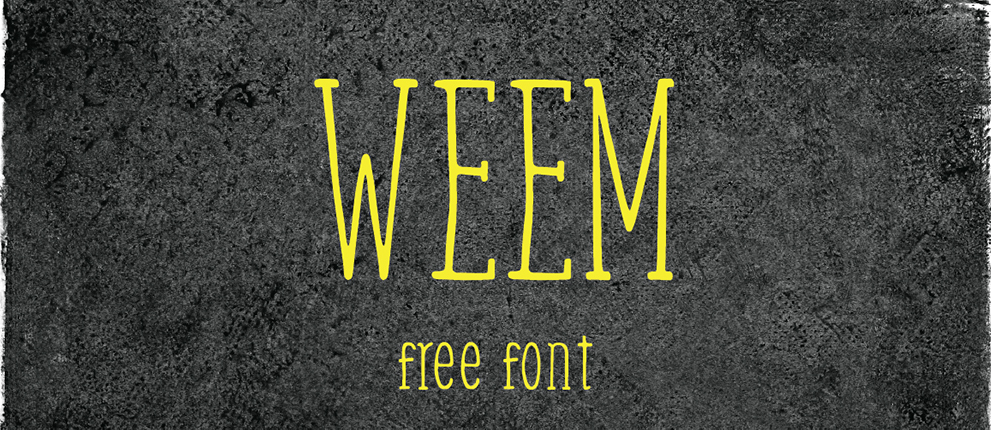
A Weem é uma fonte serif que evoca a trama suave de uma escrita feita à mão. Ela mantém um ar despojado e quase rascunhado, mas com uma estrutura robusta por trás, o que a torna ideal para projetos divertidos e, ao mesmo tempo, sérios — tanto para headlines quanto para blocos de texto pequenos. Com sua característica deslavada, a Weem é perfeita para quando você quer algo mais do que um design simples ou tradicional. Suas linhas sutilmente entrelaçadas criam um contraste interessante entre seu ar descontraído e o tom firme de uma fonte serif. É ideal para aqueles projetos que pedem tanto humor quanto seriedade, tornando-a perfeita para aplicações como logotipos, banners e mensagens em plataformas digitais. Este é um belo exemplo de uma slab serif fonte feita à mão, repleta de personalidade, adequada a uma variedade de projetos que exigem um toque único. A Weem traz ao seu projeto uma atmosfera única e vibrante, sem perder o bom comportamento necessário para textos mais formais. É perfeitamente adaptável tanto para aplicações visuais informais quanto para ambientes mais sérios, tornando-a uma escolha versátil para qualquer designer que busque uma fonte para suas necessidades digitais.